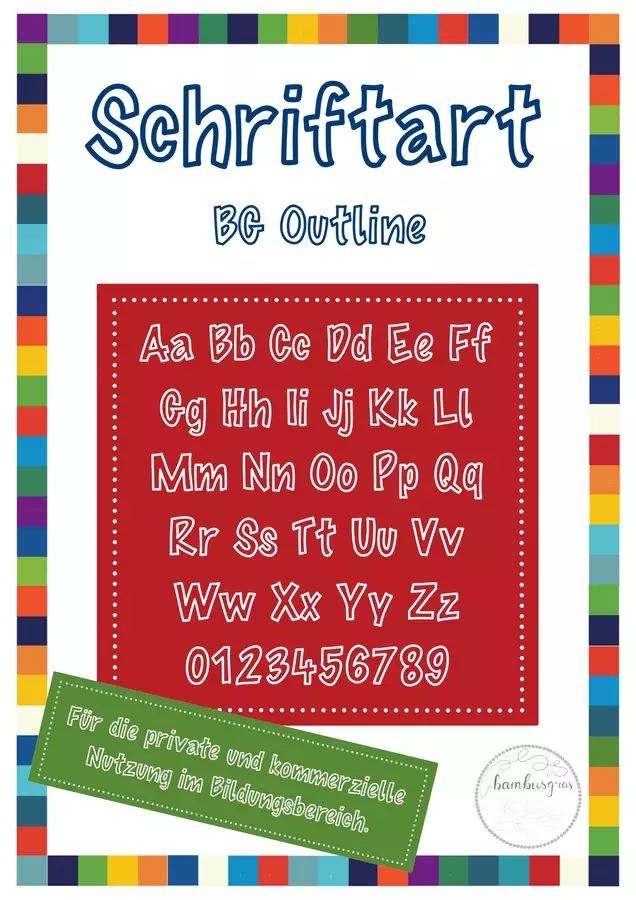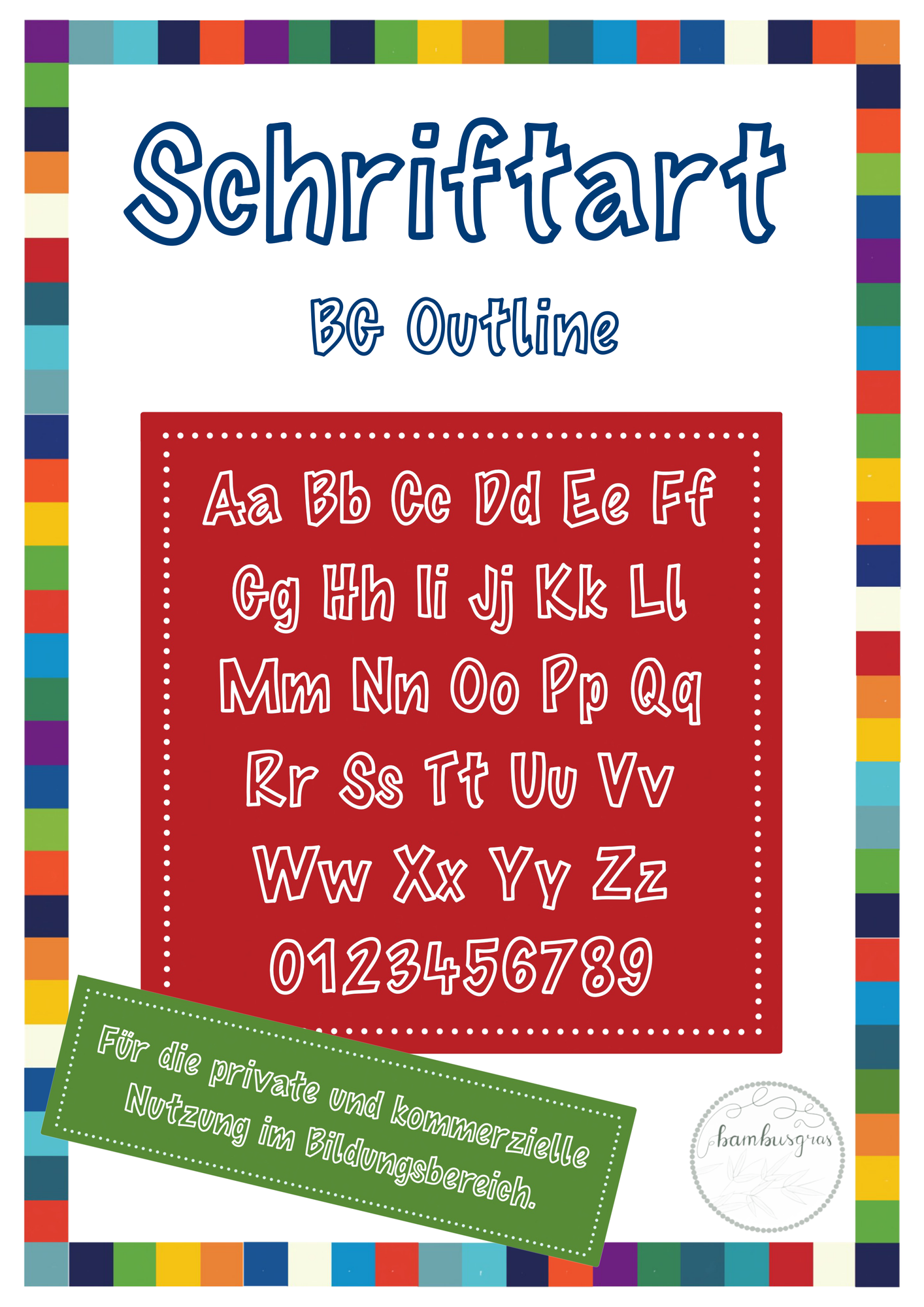
Schriftart BG Outline Font für die kommerzielle Nutzung
Jetzt gibt es die Schrift auch mit dem kleinen Druckschrift-a, was zu den anderen BG-Schriften passt! Die Kinder lieben die Schrift gerade im Anfangsunterricht zum Ausmalen - vielen Dank dafür :-)